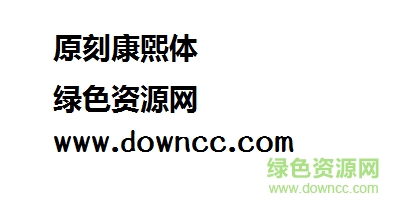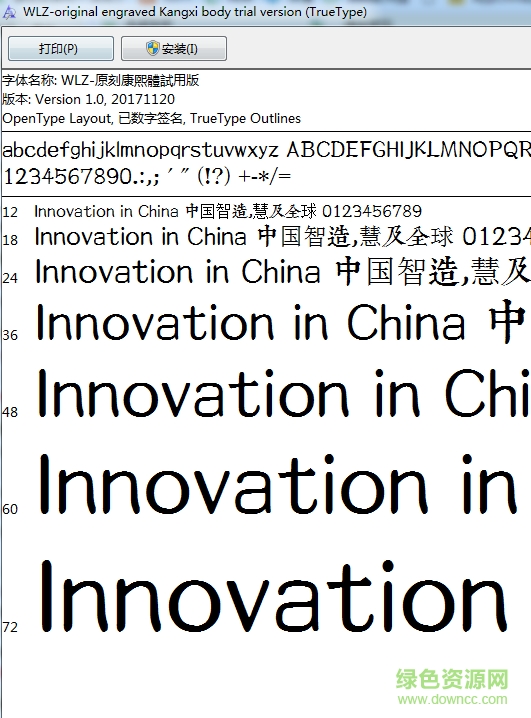
原刻康煕體字體是一款古典氣息十足的古風(fēng)字體軟件,該字體筆畫一絲不茍,工整清晰明朗大方,適用于中英文廣告設(shè)計,覺得字體好看的朋友趕緊下載使用吧!
原刻康煕體蒼勁古樸,字體樸素?zé)o華,飽含古時之風(fēng)韻,能帶給人們一種懷舊感覺,這種個性的字體適用于傳統(tǒng)產(chǎn)品,民間藝術(shù)品等主題。